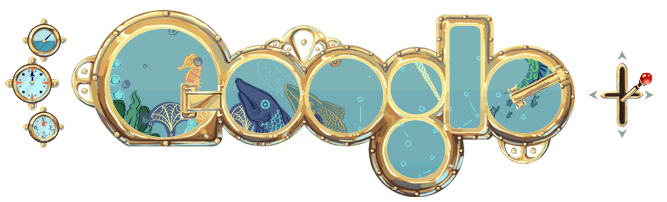
กร๊าก อาร์ตขึ้นทุกวัน
แน่จริงเอาเมาส์วาง แล้าทำให้เป็นแอริเมชั่น เซ่ โวย
ไม่ต้องแคร์ใครแล้วอะแบรนด์นี้ กร๊าก
แม่งไม่สนใจโลกแล้ว กร๊าก
คือโลโกอันก่อนๆ จะได้อารมณ์ อูวอ้าาา  กรี๊ดดดดด
แต่อัันนี้ เห็นปุ๊บ
"อะไรของเมิงงงงงง"
กร๊าก
ศิลปะในนั้นก็อารมณ์เดียวกัน  กร๊าก
GMMXIE  อู้ย..
2011 เลขโรมันน่ะครับ เกย์ออก
ปีแห่งแกรมมี่ไง
ตอนแรกคิดยังงี้นะ  กร๊าก
เจ๋งอ่ะ เลื่อนไปมาได้ด้วย  กรี๊ดดดดด
กรี๊ดดดดด
ชอบมาก เท่โคตรๆ  เจ๋ง
วันครบรอบวันเกิด 164 ปี โธมัส เอดิสัน
Google Valentine's Day 2011  ไม่ล่ะ ไม่สวยเลยแฮะ